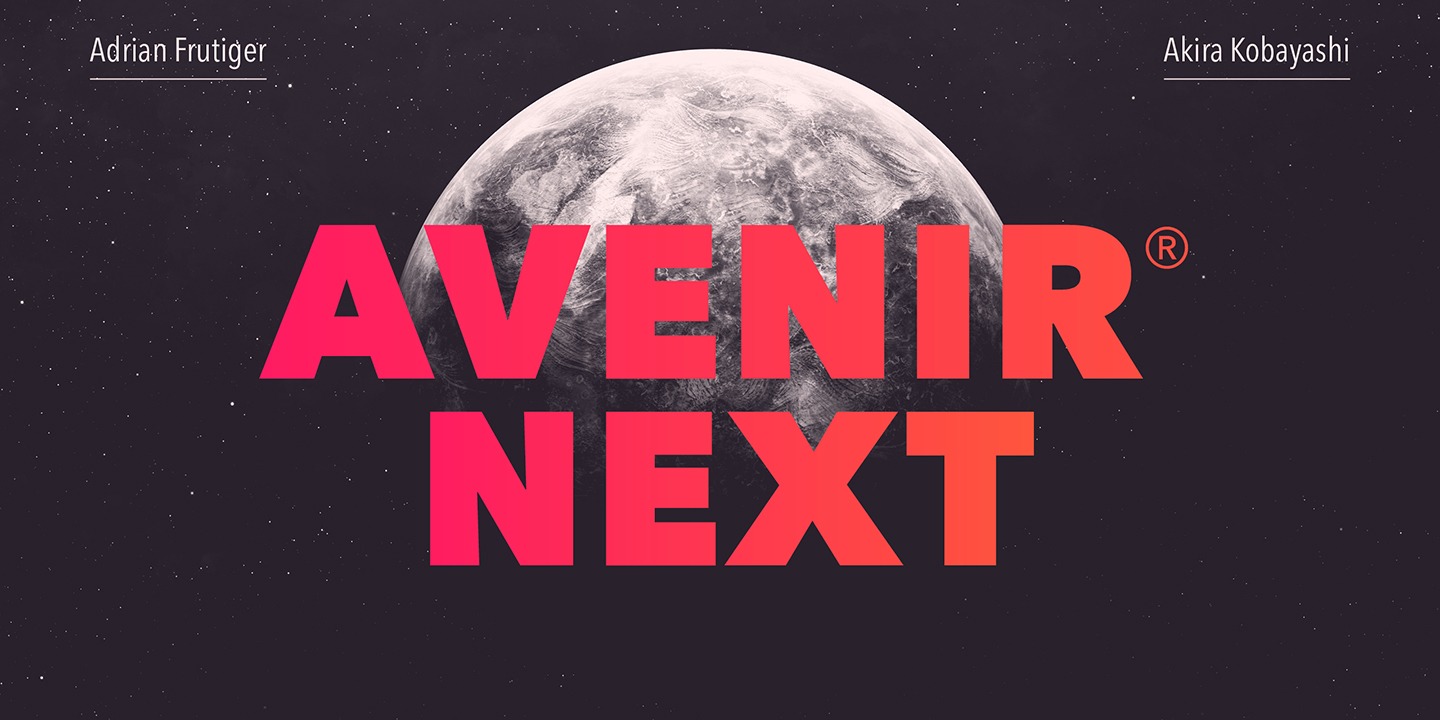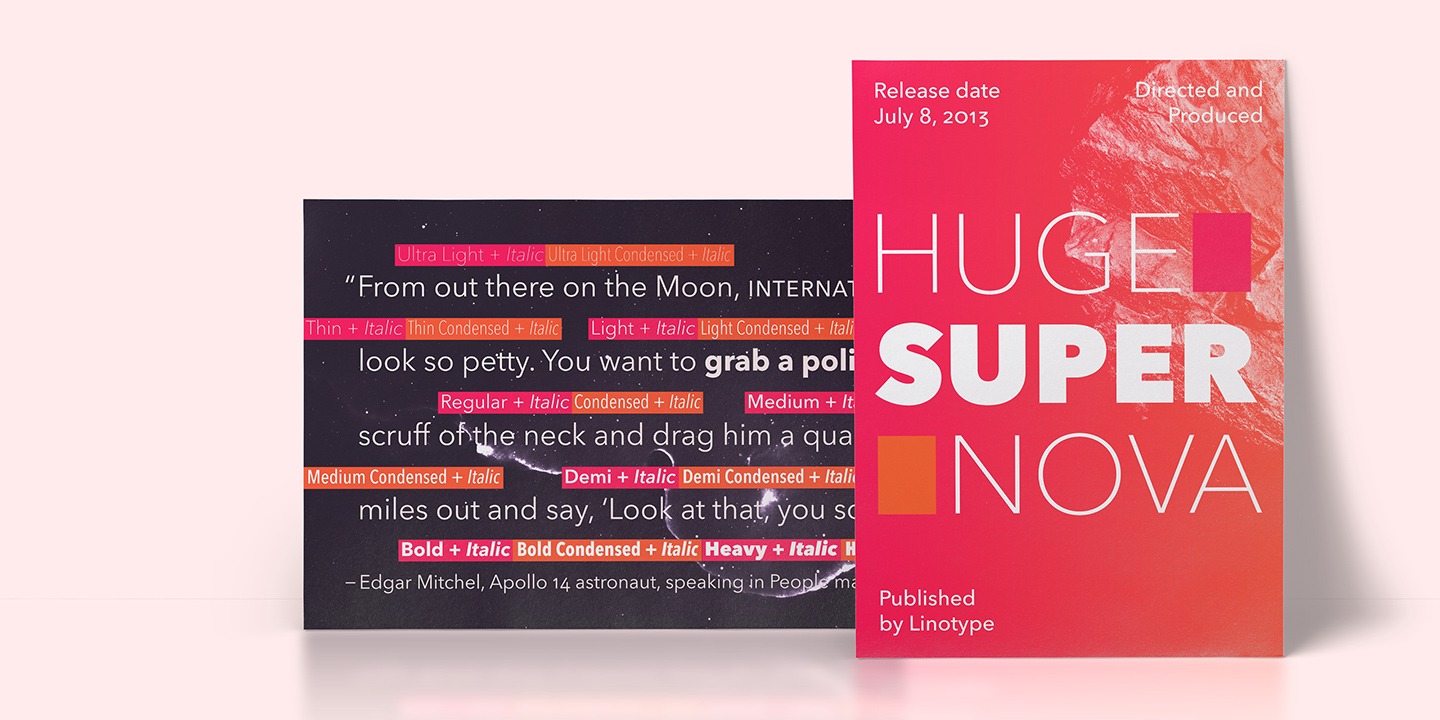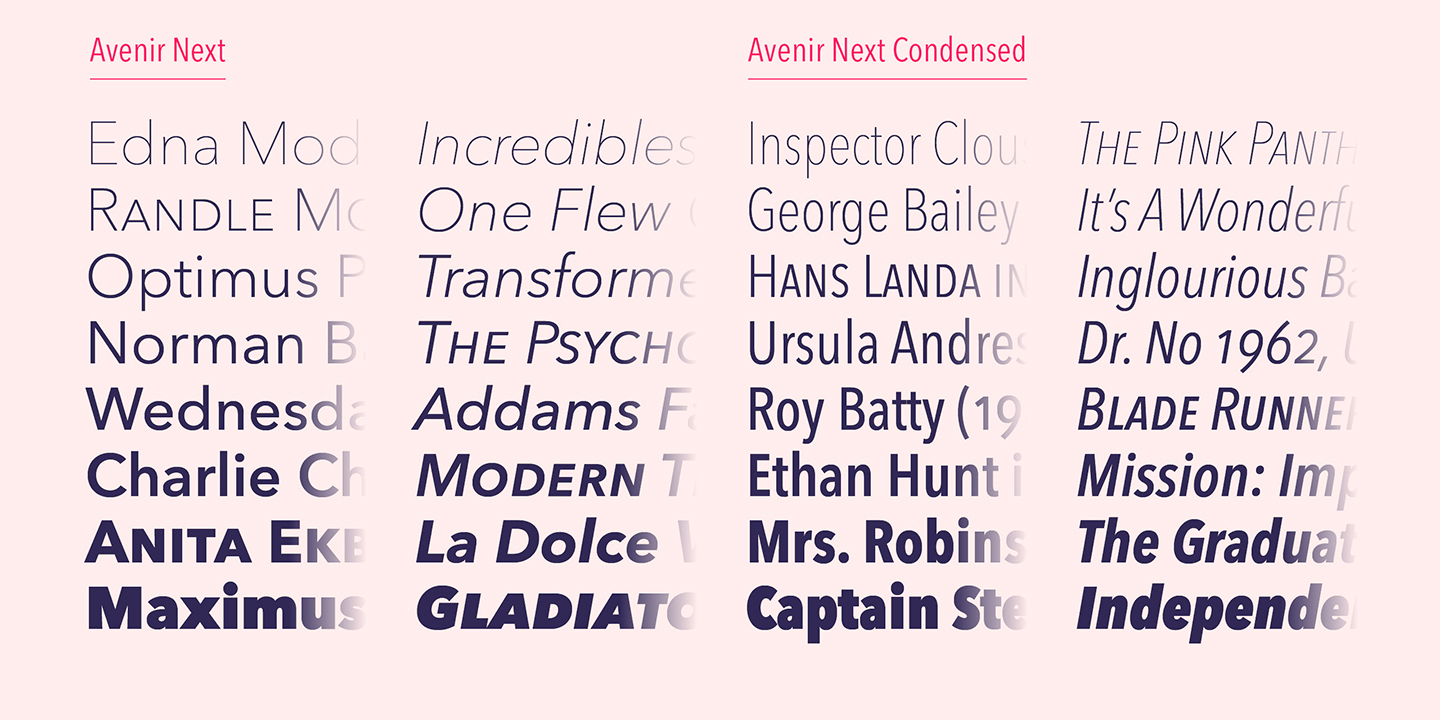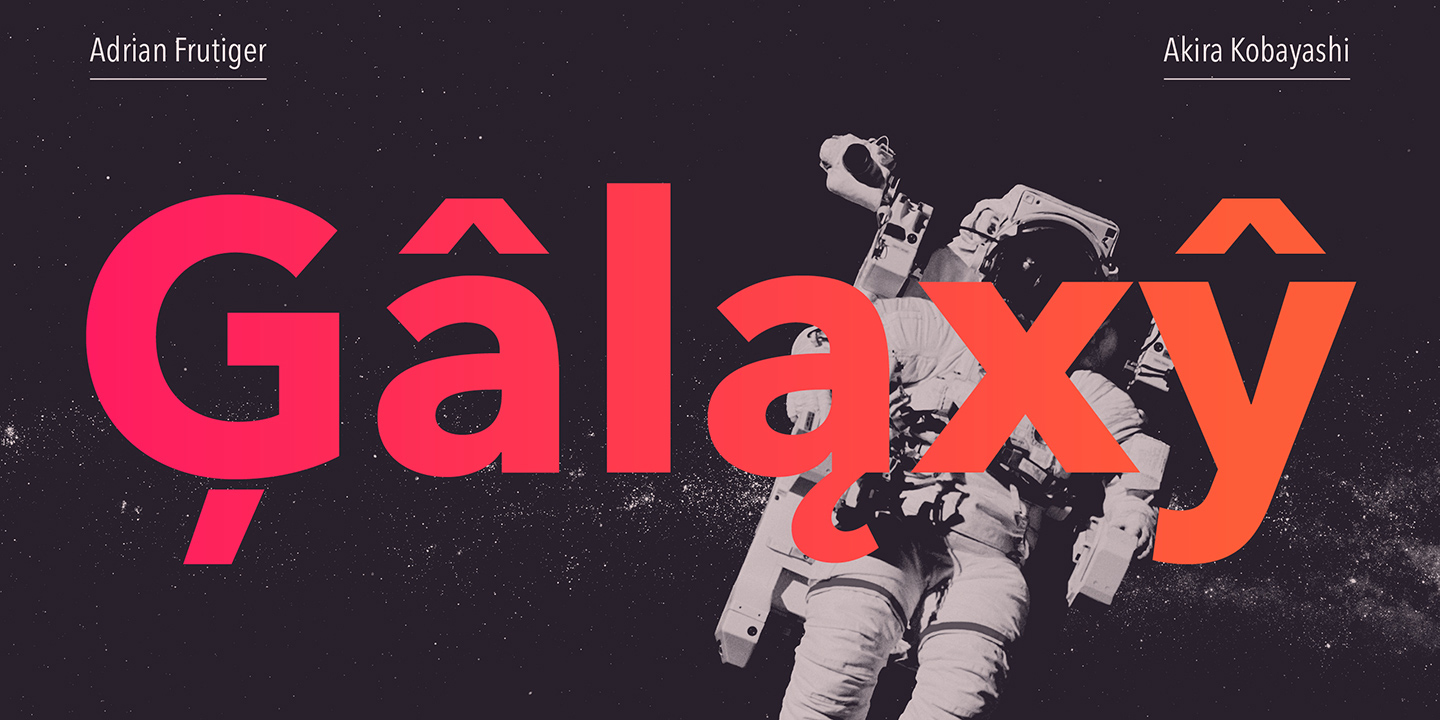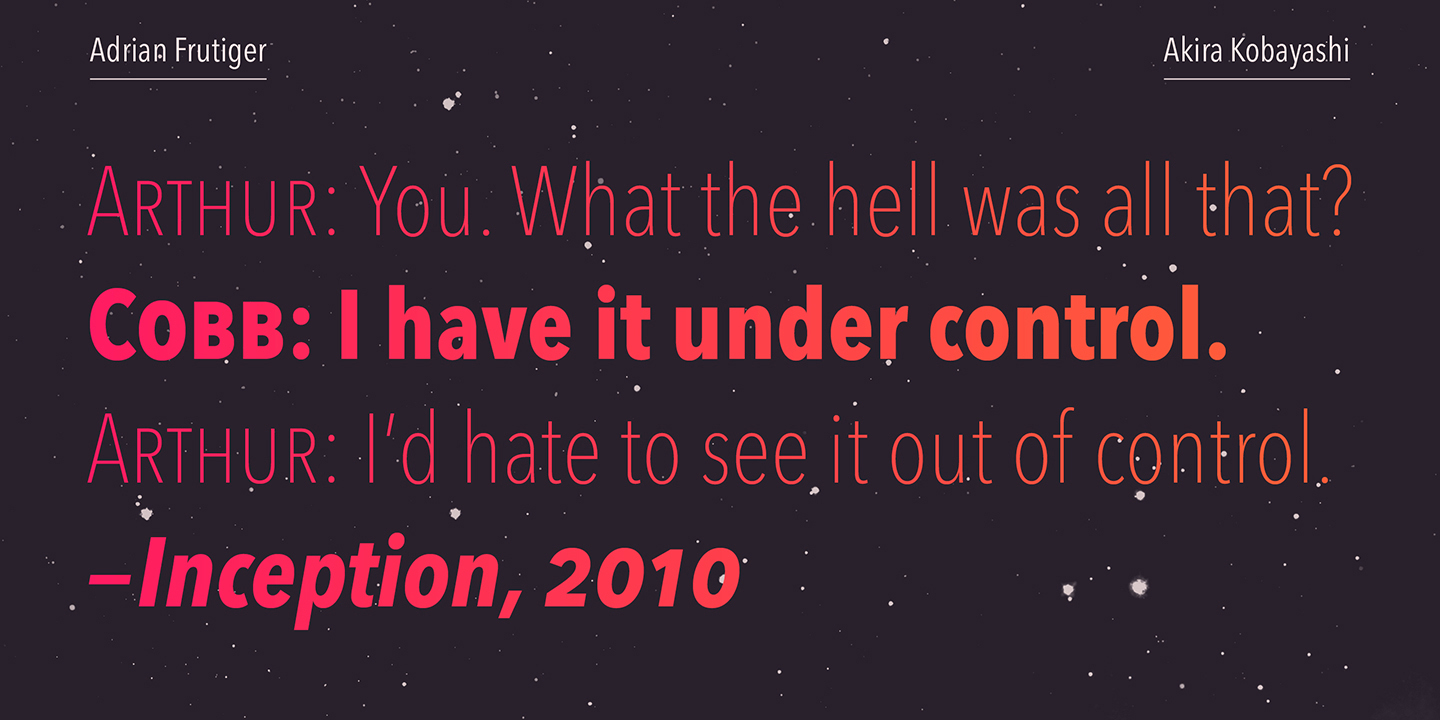
Avenir Next Pro là một sản phẩm mới mang tính hiện đại. Ngoài các kiểu tiêu chuẩn khác nhau, từ UltraLight đến Heavy, bộ sưu tập 32 phông chữ này cung cấp các thiết kế ấn tượng, phù hợp và có khả năng kết hợp tốt với rất nhiều kiểu nội dung serif hiện đại.
Nhìn chung, thiết kế của Avenir Next Pro Font Family rõ ràng, đơn giản và hoạt động tuyệt vời cho các khối nội dung và tiêu đề như nhau.
Akira Kobayashi đã làm việc cùng với người sáng tạo để tạo ra Avenir, Adrian Frutiger để đưa Avenir Next Pro vào mọi loại thiết kế. Chính khả năng của Akira trong việc đưa sự khéo léo và ý tưởng của riêng mình để mở rộng vào dự án trong khi vẫn đúng với ý định ban đầu của Frutiger, điều này khiến đây không chỉ là một kiểu chữ hiện đại mà còn đi trước thời đại.